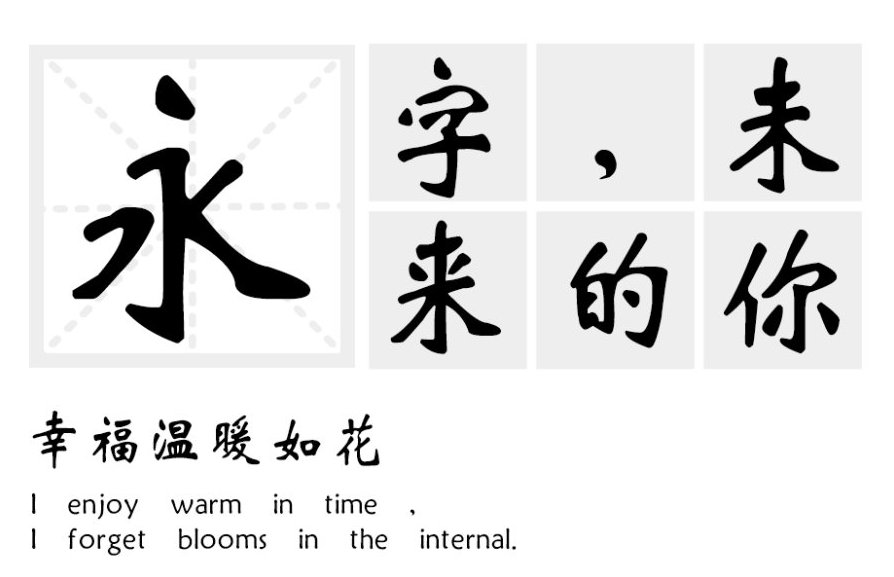
中国的书法艺术历史悠久,源远流长,名家辈出。无数知名与不知名的书法艺术家创作的艺术珍品,是中华民族优秀文化遗产的重要组成部分。今天要给大家介绍的一款 字体识别 就是“汉标新魏碑体”。
由于魏晋时期朝代文化经受着战火纷争,保存下来的只有在各地的碑志上,石窟佛像旁,高耸的山崖上,残破的砖瓦边,找到各种书体的留存,所以被称为魏碑体。这时期的书体样式、技法手段、风格流派都形成了前所未有的辉煌和影响。
“汉标新魏碑体”将传统魏碑的苍劲、硬朗、险峻与现代黑体的方正、简洁、朴实融合在一起,并强化了折笔处的外方内圆,撇、捺的收笔处带有装饰性饰角。这款字体的风格外刚内柔,适用于书刊标题、广告和产品包装、logo设计。